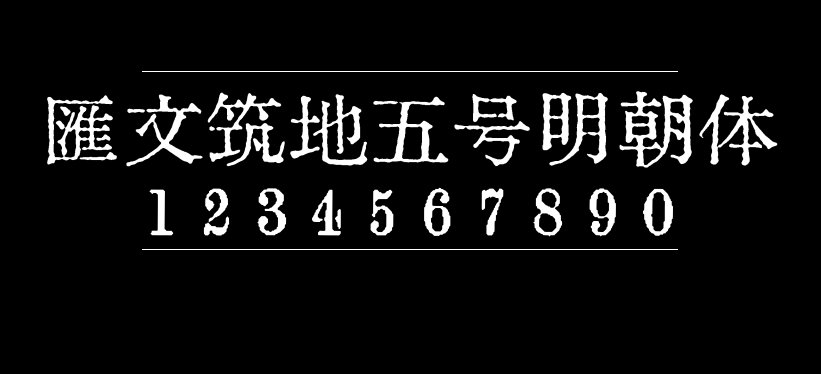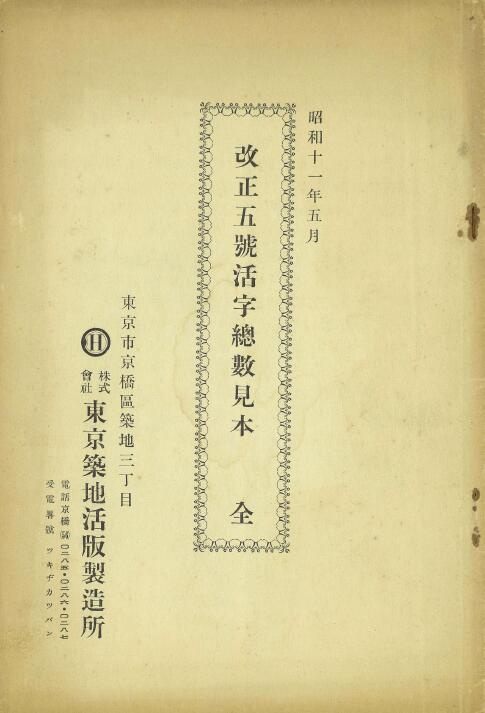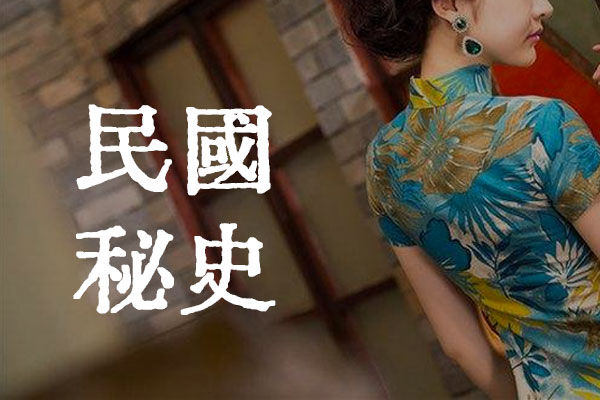
汇文筑地五号明朝体
汇文筑地五号明朝体(Huiwen-Tsukiji-5-mincho)是百度旧字形吧吧主天王帝廷发布的一款免费商用字体,字形来源于《改正五号活字总数见本 全》这本古籍(日本昭和11年1936年东京筑地活版製造所出版),其字形是现在日本明朝体之源流,和当时中国的铅字字形一样源自于康熙字典的字形。
由于这款字形是从古籍复刻过来,所以古籍中没有的字,在字体文件中也就没有。简体字包含5547个,繁体字相对更多更全一些。这款字体适合古风场合,很有历史感,跟康熙字典有点像,感谢作者的无私共享!